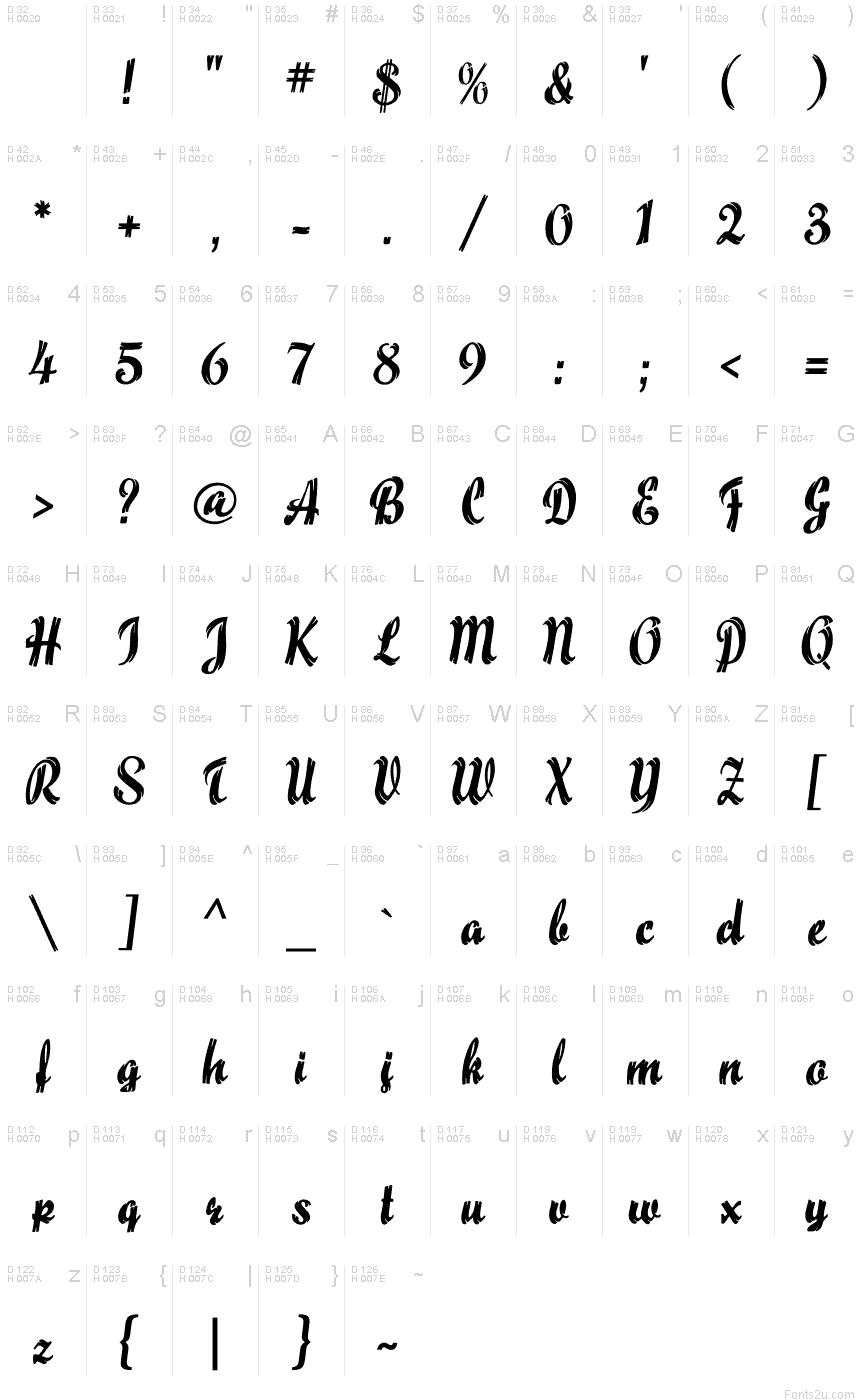
Maize Regular
Maize autorstwa Richarda Williama Muellera to darmowy krój typu brush, stworzony na bazie szybkich, pochyłych pociągnięć i luźnego, odręcznego rytmu. Litery wyglądają jak nakreślone mocno nasączonym markerem, z surowymi krawędziami i zwężającymi się łukami, które nadają im energię, a nie wygładzony wygląd.
Ten ruch sprawia, że krótkie nagłówki naturalnie prezentują się na plakatach, opakowaniach produktów, menu kawiarnianych, ulotkach czy w luźnym brandingu. Dzięki temu, że pociągnięcia lekko urywają się na krawędziach zamiast być gładkie, Maize ma w sobie odpowiednią dozę chropowatości dla okładek albumów czy grafik promocyjnych, które potrzebują bezpośredniego, odręcznie malowanego charakteru.